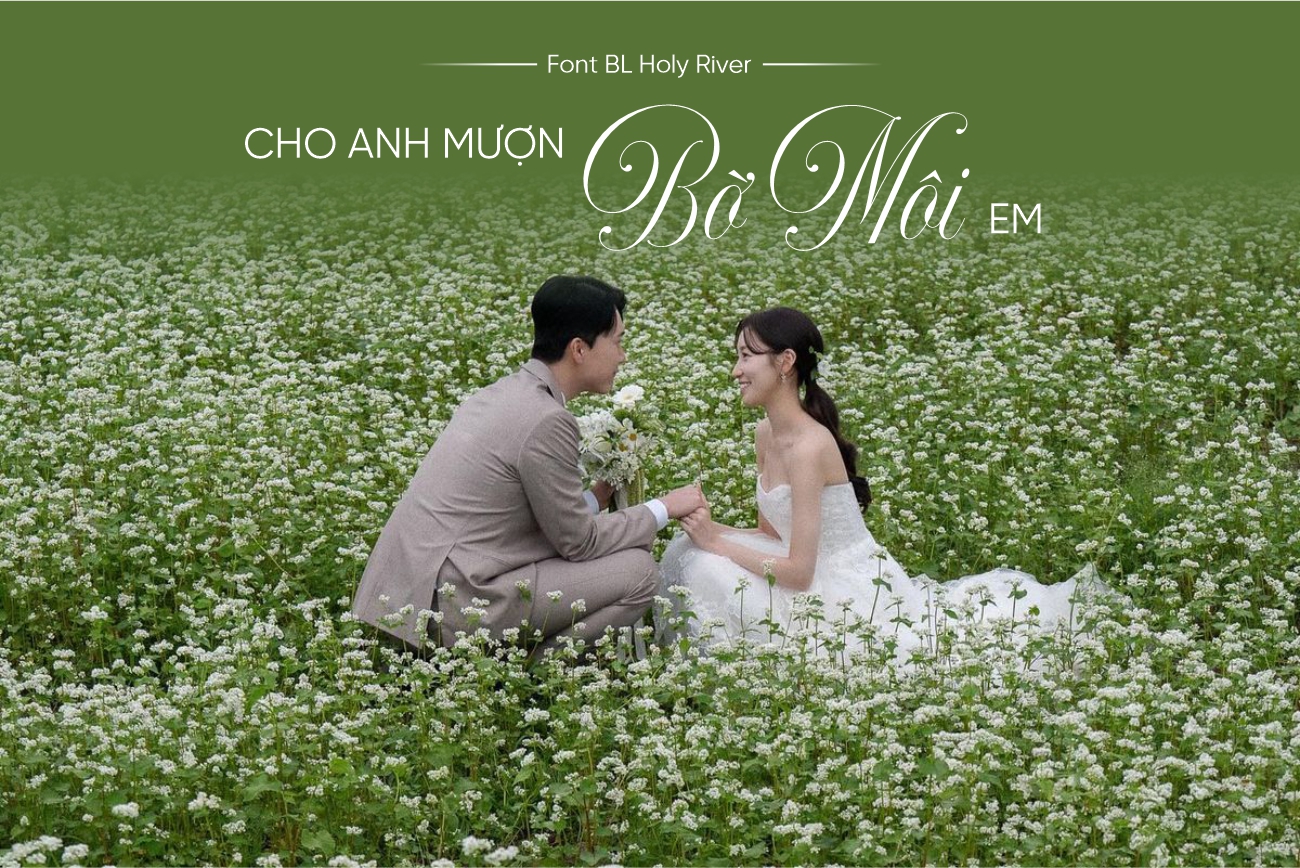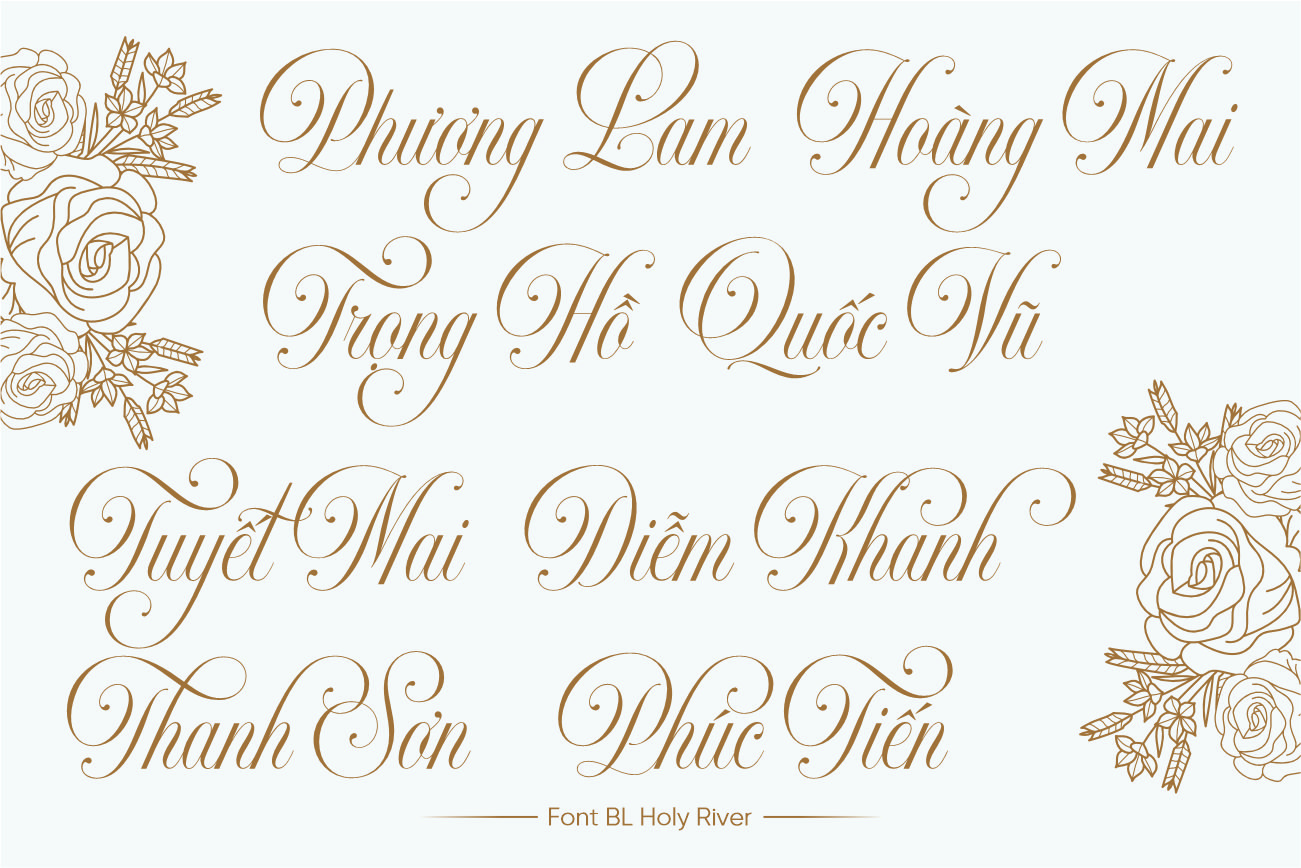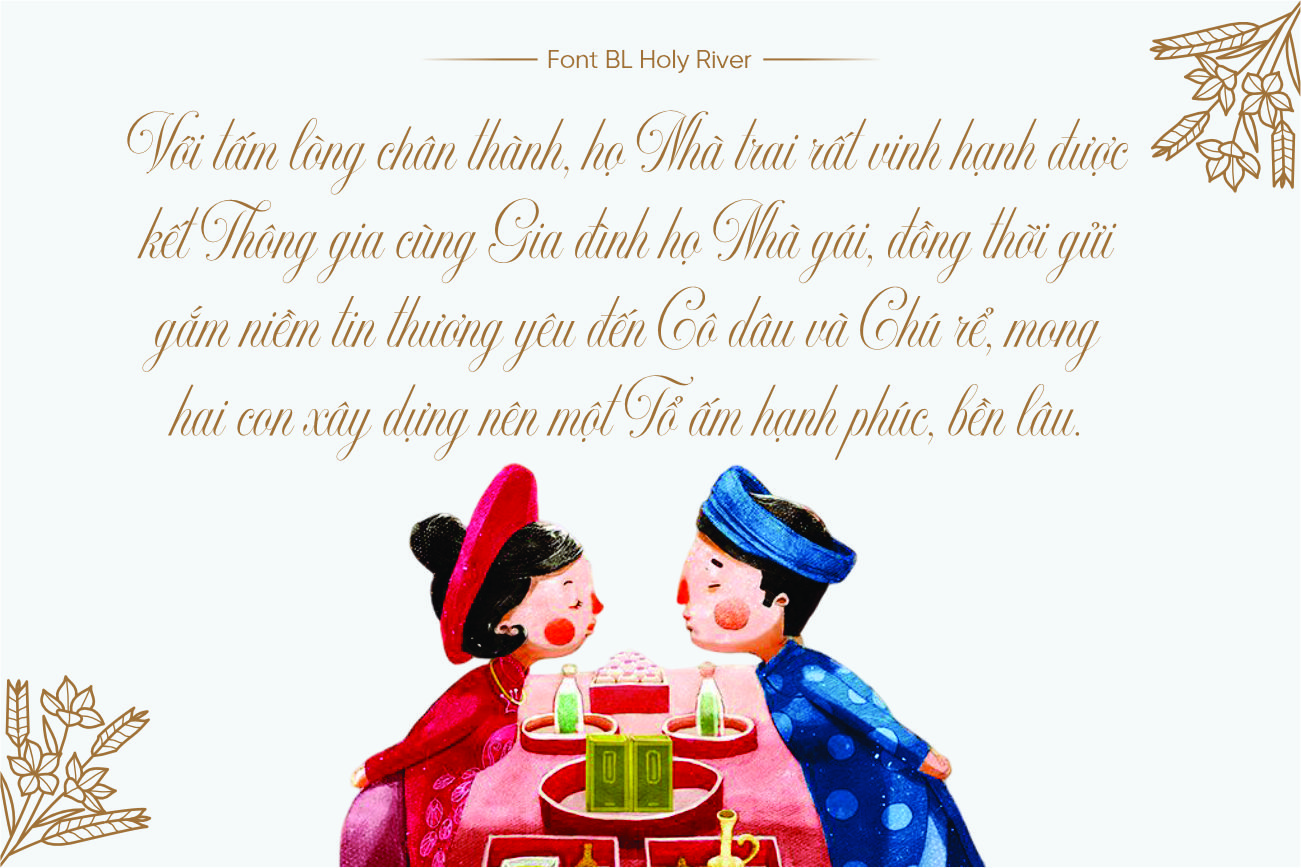
Font chữ viết tay dành cho thiệp cưới BL Holy River Việt hóa sang trọng
Trong thế giới của các nhà thiết kế, việc tìm kiếm một bộ chữ vừa mang hồn cốt cổ điển vừa giữ được nhịp sống đương đại luôn là một hành trình thú vị. BL Holy River — phiên bản Việt hóa từ tác phẩm gốc Holy River của nhà thiết kế tài hoa Andrey Sharonov — chính là câu trả lời hoàn hảo cho hành trình đó. Được Team BL chăm chút tỉ mỉ từng dấu câu, bộ font này không chỉ đơn thuần là một công cụ trình bày mà còn là một tác phẩm nghệ thuật, mang đến kiểu dáng thanh lịch và đẳng cấp cho mọi ấn phẩm truyền thông hay thương hiệu.
Nhìn vào BL Holy River, người xem dễ dàng bị cuốn hút bởi những đường nét uốn lượn mềm mại, mang đậm phong cách calligraphy truyền thống. Đây là dòng font script mô phỏng nét bút lông thủ công với sự biến thiên độ dày mỏng đầy nhịp điệu. Sự kết nối giữa các con chữ được tính toán một cách nghệ thuật, tạo nên một dòng chảy tự nhiên như tên gọi "Holy River" (Dòng sông linh thiêng). Chính sự uyển chuyển này đã tạo nên một tổng thể vừa bay bổng, vừa giữ được sự chỉn chu cần thiết cho các yêu cầu thiết kế chuyên nghiệp.
Nguồn gốc của font chữ bắt nguồn từ cảm hứng của Andrey Sharonov về nghệ thuật thư pháp châu Âu, nơi mỗi ký tự đều mang một cá tính riêng biệt. Tác giả đã khéo léo lồng ghép sự phóng khoáng của nét vẽ tay vào cấu trúc chữ hiện đại, giúp font chữ không bị rơi vào cảm giác cũ kỹ. Khi được Team BL thực hiện Việt hóa, tinh thần này vẫn được giữ vững, đồng thời tối ưu hóa các dấu tiếng Việt sao cho hài hòa nhất với kiểu dáng thanh lịch nguyên bản, giúp người dùng thoải mái sáng tạo mà không gặp bất kỳ rào cản nào về thẩm mỹ hay kỹ thuật.
Với vẻ đẹp tinh tế đặc trưng, BL Holy River cực kỳ phù hợp cho các không gian thiết kế đòi hỏi sự sang trọng như thiệp mời sự kiện cao cấp, logo mỹ phẩm, hay các bìa tạp chí thời trang. Đặc biệt, khi ứng dụng vào các câu trích dẫn (quotes) hay tiêu đề lớn, phong cách calligraphy của bộ font sẽ tỏa sáng rực rỡ, tạo nên điểm nhấn thị giác mạnh mẽ nhưng vẫn vô cùng dễ chịu. Sự đan xen giữa các nét thanh mảnh và nét đậm dứt khoát giúp bộ chữ có chiều sâu, dễ dàng chinh phục ánh nhìn của bất kỳ ai ngay từ lần chạm mặt đầu tiên.
BL Holy River là một minh chứng cho sự giao thoa tuyệt vời giữa kỹ thuật số và nghệ thuật thủ công. Sự đầu tư nghiêm túc từ khâu thiết kế gốc đến quá trình Việt hóa đã mang lại một công cụ đắc lực cho cộng đồng sáng tạo tại Việt Nam. Dù bạn đang xây dựng một bộ nhận diện thương hiệu hay đơn giản là trang trí một tấm thiệp cá nhân, bộ font với kiểu dáng thanh lịch này chắc chắn sẽ giúp thông điệp của bạn trở nên sống động, giàu cảm xúc và đầy tính nghệ thuật.